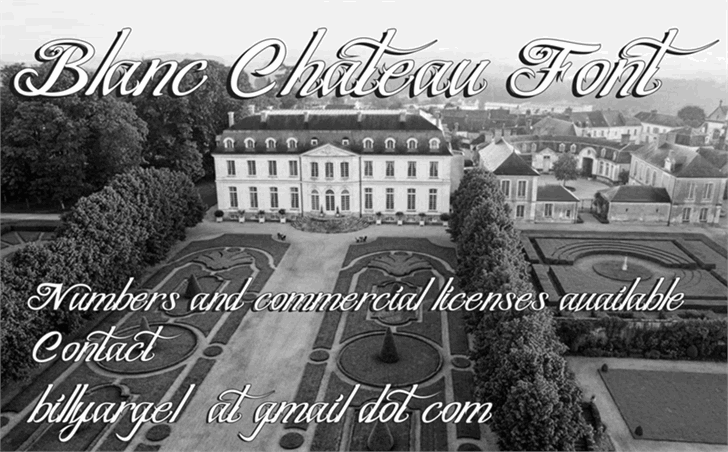
BLANC CHATEAU Font é uma elegante tipografia serifada criada por Hamilton para designers que desejam adicionar textura sofisticada a seus projetos de calligrafia. Inspirado na arquitetura e no design clássico, esse font se destaca em sua capacidade única de proporcionar um tom elegante e moderno ao texto. A personalização da Linha BLANC CHATEAU permite que designers adaptem suas criações à perfeição, sem perder a essência dos padrões históricos. Este font é ideal para projetos de design gráfico, arte digital, publicidade e mais ainda, oferecendo uma solução versátil e sofisticada. Com sua design minimalista e arquitetura clara, BLANC CHATEAU Font combina perfeitamente com várias técnicas de design. Seja você um designer ou artista digitado, este font traz uma nova dimensão à sua obra, permitindo-lhe criar textos que se destacam em qualquer cenário visual. Engajante e versátil, BLANC CHATEAU Font é a escolha perfeita para aqueles que desejam adicionar um toque de sofisticação ao seu trabalho. Para mais informações ou para visitar o site oficial do designer Hamilton, basta acessar [EMAIL PROTECTED] e [URL] billyargel.com.